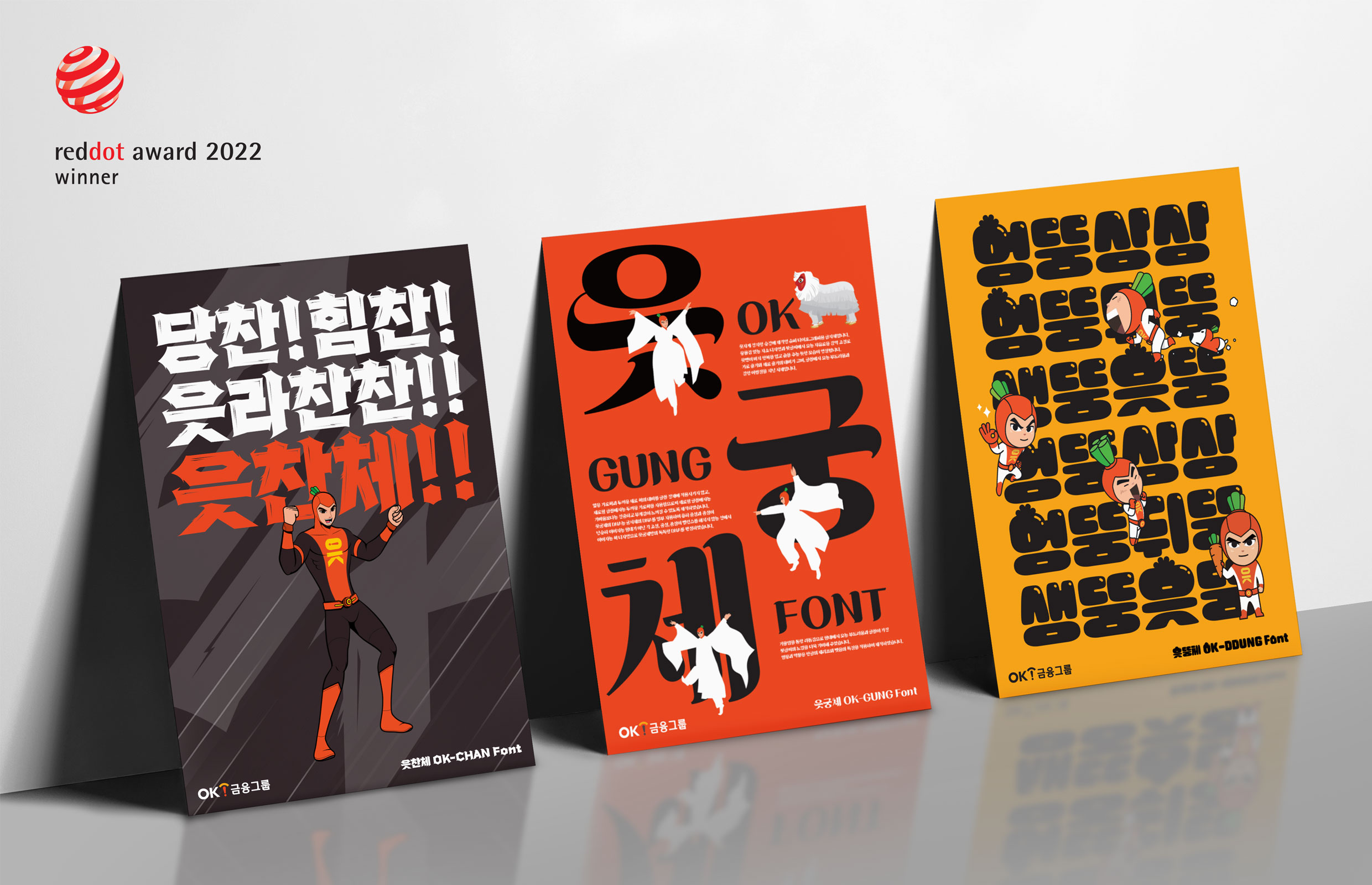
OK금융그룹 서체 '읏맨체', '레드닷 어워드' 수상
OK금융그룹이 '2022 레드 닷 어워드'에서 회사의 캐릭터 서체 '읏맨체'가 브랜드·커뮤니케이션 분야 본상을 수상했다고 8일 밝혔다.
1955년 시작된 레드닷 어워드는 디자인의 혁신성과 독창성 등을 종합적으로 평가하는 세계적인 디자인 공모전이다.
△iF 디자인상 △IDEA 디자인상과 함께 세계 3대 디자인상 중 하나로 꼽힌다. 앞서 OK금융그룹은 지난 5월15일 세종대왕탄신일 625주년을 맞아 윤디자인그룹 계열사인 '엉뚱 상상'과 협업해 '읏맨체'를 선보였다.
읏맨체는 OK금융그룹 캐릭터인 '읏맨'의 목소리를 시각화 한 캐릭터 서체로 △읏찬체 △응궁체 △응뚱체 등 3가지로 구성됐다. 읏찬체는 읏맨의 힘차고 강한 에너지를 담았으며, 읏궁체는 곡선을 디자인 모티브로 삼아 우아함을 표현했다. 읏뚱체는 읏맨의 기발함과 엉뚱함을 동글동글하게 구현했다.